Yazar ve tipograf Sarah Hyndman, Londra’da V&A’de (Victoria ve Albert Müzesi) yaptığı ankette tipografi ve “değer” arasındaki ilişkiyi araştırmış. Hyndman, bir yazı fontunun bir ürünü daha pahalı gösterip gösteremeyeceğini araştırdığı çalışması aynı zamanda tipografik karakterlerin aynı şekilde bir ürünü ucuzlatıp ucuzlatmadığını da sorguluyor.
Yaklaşık 368 kişi ile yapılan anket sonucuna göre; kalın fontlar ve eski MS Dos’tan hatırlayacağımız sert Terminal gibi fontlar ürünlerde daha ucuz algısı yaratırken; Serif ve Contrast serileri gibi daha yumuşak fontlar ürünlere daha yüksek rakamlı etiketler takılmasını kolaylaştırıyor.
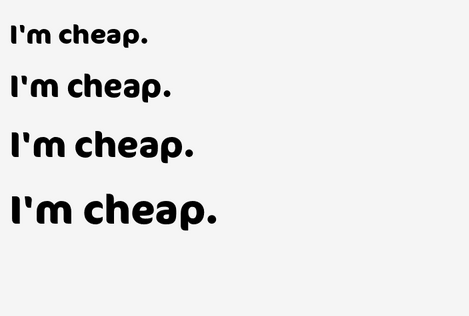
Yine bu araştırmaya göre, Didot yazı karakteri de fontlar içinde en değer katan font tipi çıkmış. Burada lüks ve ucuz markalarla karşılıklı besleme süreci de etkili. Örneğin; Serif yazı karakteri çoğunlukla moda ile ilişkilendiriliyor, Vogue, Harper’s Bazaar gibi ünlü moda dergilerinde sıkça kullanılıyor ve artık ortak bilinçte bu yazı tipi lüks ürünlerle ilişkileniyor.
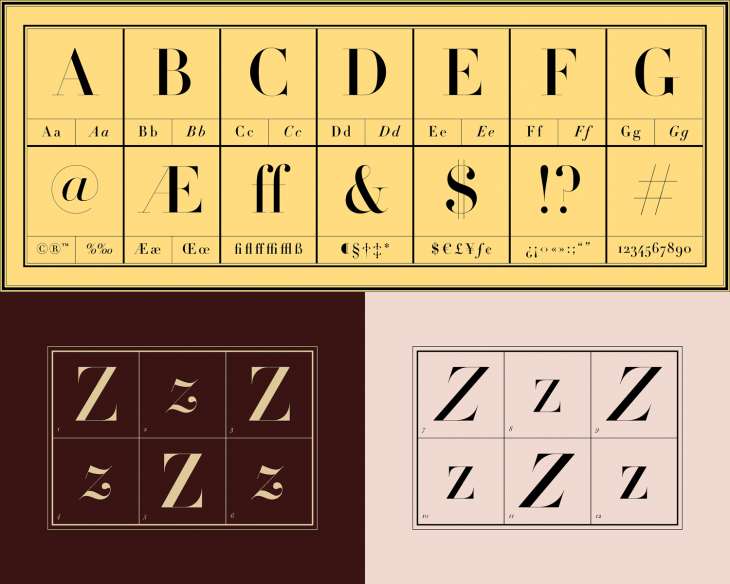
İnsanlar üzerindeki bu algının geleneksel olarak belli fontların lüks ürünlerle olan ilişkisi ve kullanımı sonucu ortaya çıktığını belirten Hyndman,”Cocon Bold” yazı tipinin en “ucuz” algılı fontlardan olmasını şaşırtıcı bulmuş. “VAG Rounded Light” da ucuz algılanan fontlar grubunda yer alıyor, Hyndman için bu da ilginç bir sonuç olmuş çünkü genellikle yumuşak yazı karakterleri daha pahalı bir algı yaratıyormuş.
Ancak bu yazı tiplerinden genellemeye gitmenin çok da sağlıklı olmayacağı konusunda da uyarılar var: Öncelikle estetik anlayışın evrimi devam ettiğinden, tercihler yavaş da olsa değişim gösteriyor, ayrıca eskime faktörü de etkin; yani devamlı kullanılan fontlar bir süre sonra eski hissi uyandırarak tüketici üzerindeki daha çok para harcatma etkisini kaybedebiliyor.
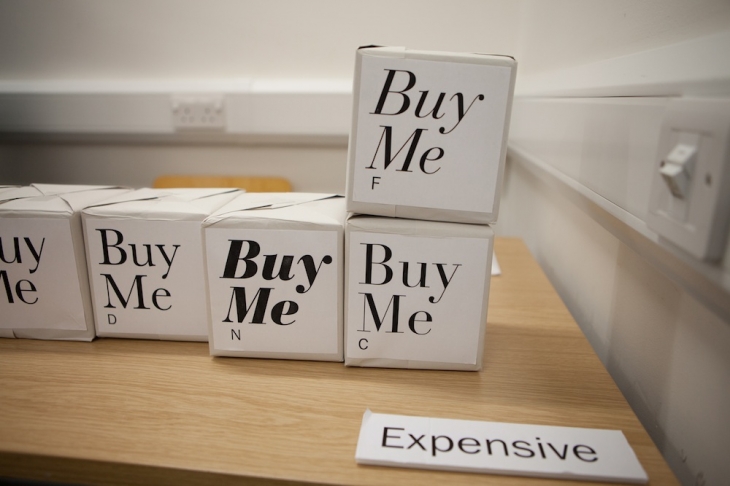
Bu durumun tersi de geçerli, bazı “ucuz” fontlar yeniden yorumlanarak lüks ürünlerle eşleşebiliyorlar. Honor markası font olarak ucuz görülen Compacta’yı yeniden yorumlamış ve sonuçta ürünle birbirlerini yükselten bir font elde edilmiş. Burada font ve ürünün uyumundan söz etmek gerek ve bu da kategorizasyonu zorlaştıran bir olgu olarak karşımızda. Tipograf Johnathan Hoefler, en iyi fontu farklı bir tonda konabilen ve sırtında farklı paketler taşıyabilen olarak tanımlamış. Bu açıdan bakınca tüm fontlar üzerinde çalışarak kendine uygun markaların ve ürünlerin bir biçimde sesi olabilirler.